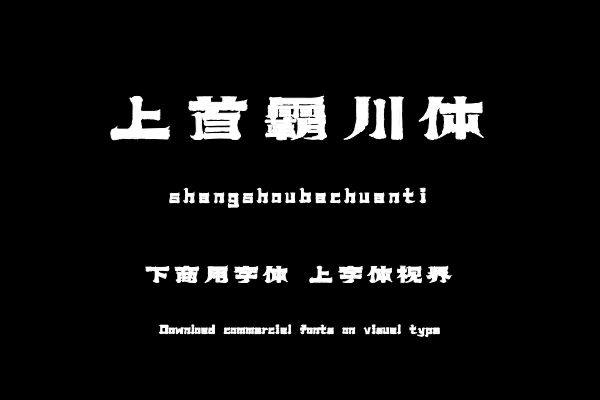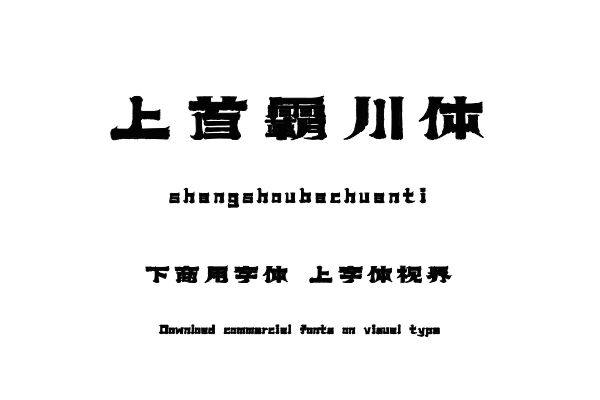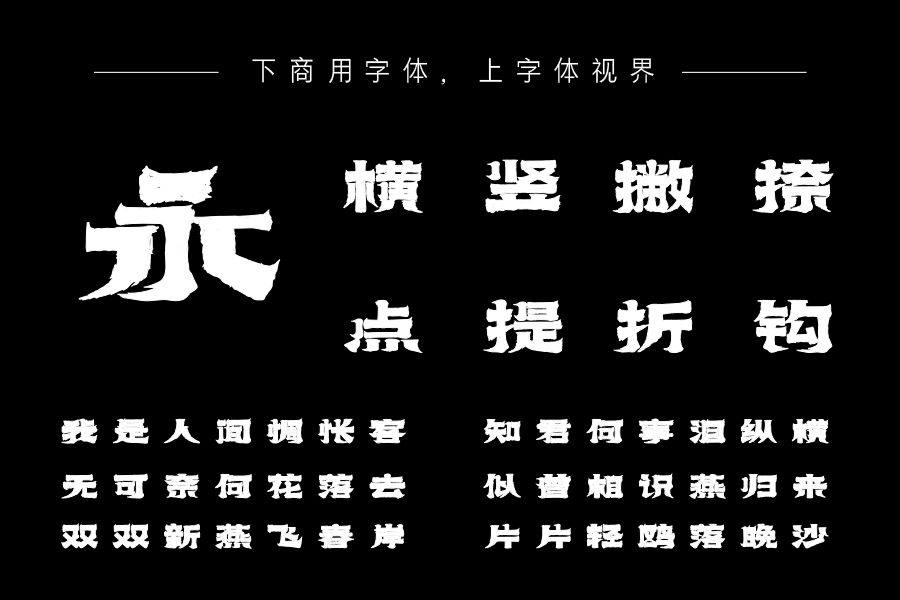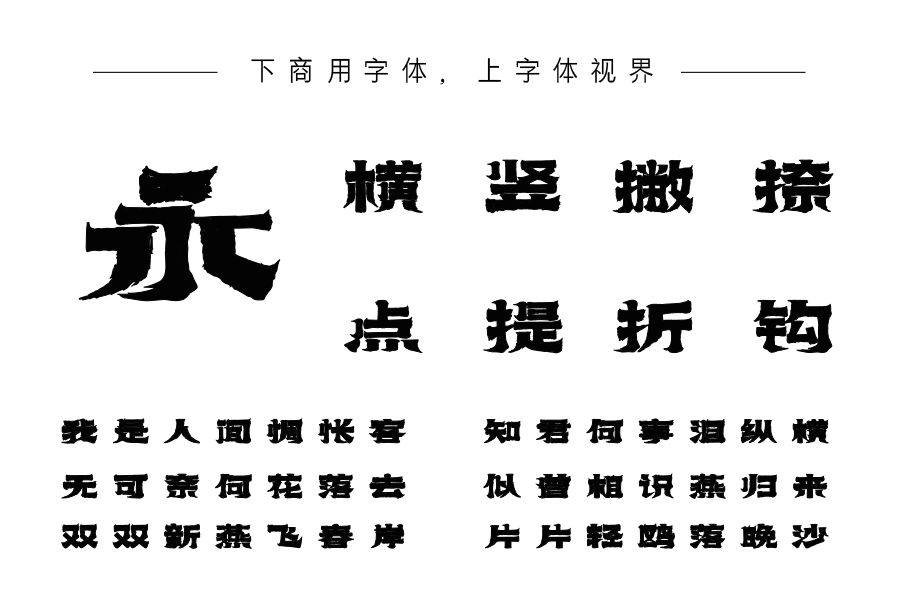
上首霸川体,字体采用了毛笔书法的笔触,粗细变化明显。每一笔都像是用毛笔一气呵成,充满了动感和力量。粗重的笔画体现了稳重和坚定,而纤细的笔画则增加了字体的灵动感。......购买须知:“下载服务费”与“字体VIP”所获得字体 仅用于个人非商用, 商用请联系付费授权。本字体为电脑用字,手机没有root权限不支持直接手机换字(手机如何root,请自行百度搜索教程)。购买前请先 了解清楚后再付款 ,字体为虚拟产品无法回收 一旦购买不支持退款。